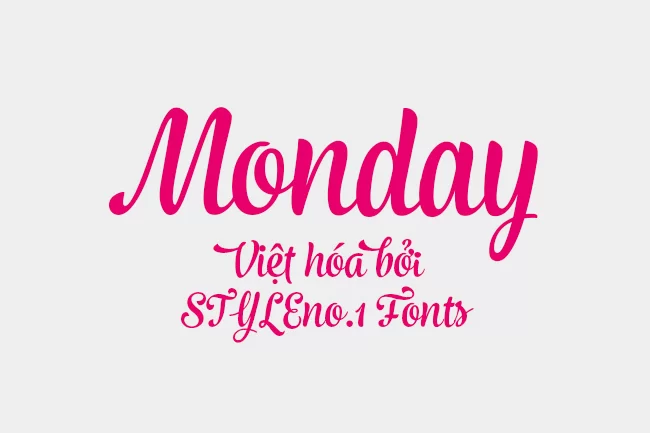
SVN Monday là một Font chữ đậm và mạnh mẽ cùng bộ trang trí phù hợp. Font chữ có một cảm giác chữ viết tay năm 1950 nó khá lý tưởng cho các mục đích như thiết kế logo, bao bì và thiết kế thương hiệu.
Nhà thiết kế: Emil Karl Bertell
Nhà phát hành: Fenotype
Việt hóa: STYLEno.1 Fonts